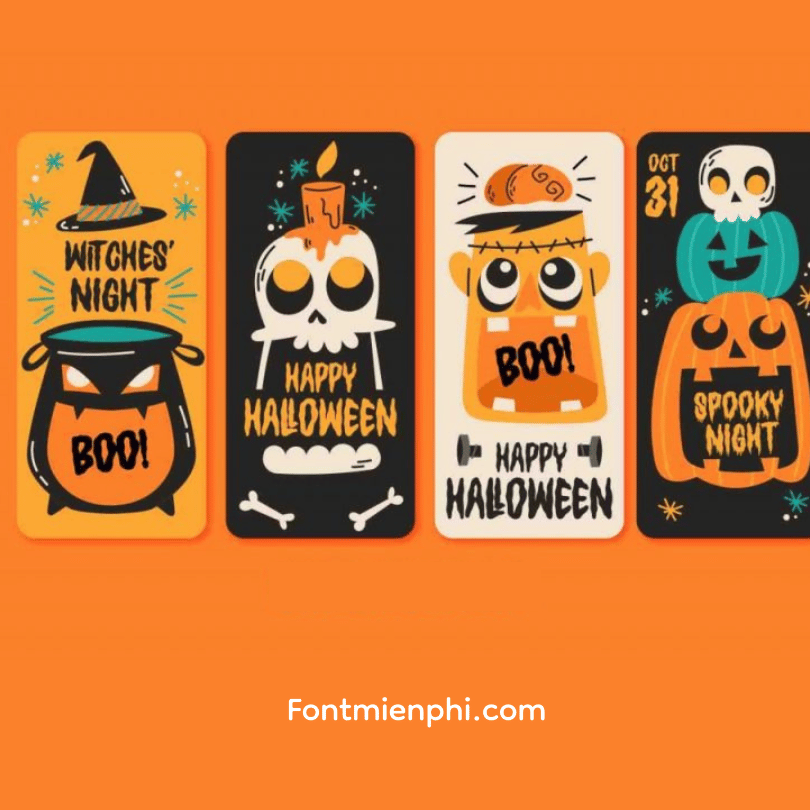
Việt hóa font 1FTV VIP Ghoulies kiểu Halloween
Việt hóa font 1FTV VIP Ghoulies kiểu Halloween – Phông Chữ Halloween Kinh Dị Đỉnh Cao
1FTV VIP Ghoulies là font chữ Việt hóa chuyên nghiệp với phong cách Halloween cực chất, mang đậm chất kinh dị và huyền bí. Với những nét chữ sắc nhọn như móng quỷ kết hợp hiệu ứng bóng ma, font chữ này sẽ khiến mọi thiết kế của bạn trở nên đáng sợ và ấn tượng hơn bao giờ hết!
ĐẶC ĐIỂM NỔI BẬT:
✔ Hỗ trợ tiếng Việt chuẩn Unicode – phù hợp mọi nhu cầu thiết kế
✔ Phong cách kinh dị đậm chất Halloween – nét chữ quỷ dị, sắc nhọn đầy ám ảnh
ỨNG DỤNG HOÀN HẢO:
• Thiết kế poster phim kinh dị, Halloween
• Bìa sách/truyện ma, tạo hình nhân vật quỷ dị
• Thiệp mời tiệc Halloween đáng sợ
• Thiết kế áo thun, vật phẩm Halloween